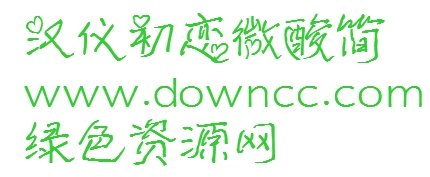
漢儀初戀微酸簡(jiǎn)是一款有著溫柔筆觸的初戀情書字體,給人時(shí)光與眼前人靜好的溫暖體驗(yàn),蘊(yùn)含著不可訴說的少女情懷,喜歡的朋友就來綠色資源網(wǎng)試試吧!
有這樣一種滋味,甜似初戀般的微酸……
初戀微酸體讓部分字體增加了可愛的心型圖案,卻不顯得雜亂紛呈之感,字里行間跳動(dòng)的都是醉人的初戀氣息,讓你閱讀文字時(shí)都會(huì)心微笑著!